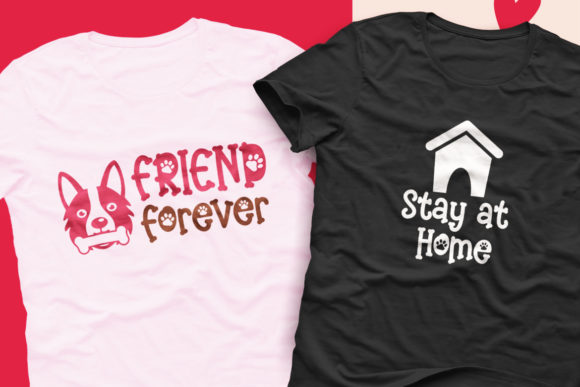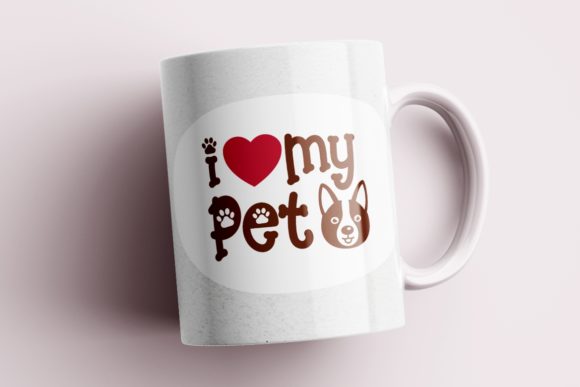
可愛英文字體
家裡有養狗,或者正在設計寵物相關的商品、卡片,今天這款限時免費字體你一定不能錯過啊!Creative Fabrica 今日限免活動推出了 Paw Wow,充滿趣味的狗狗主題展示字體,內建可愛的狗爪圖案,光是看著就讓人心情變好。售價原本要 $15 美元,今天免費!
Paw Wow 是一款展示 (Display) 字型,由設計師 HansCo 創作,字體最大特色是字母之間融入了狗狗插圖元素,整體風格活潑可愛,帶點手繪質感,用來做標題或主視覺文字效果非常突出。評分為 4.9 顆星 (22 則評價)。